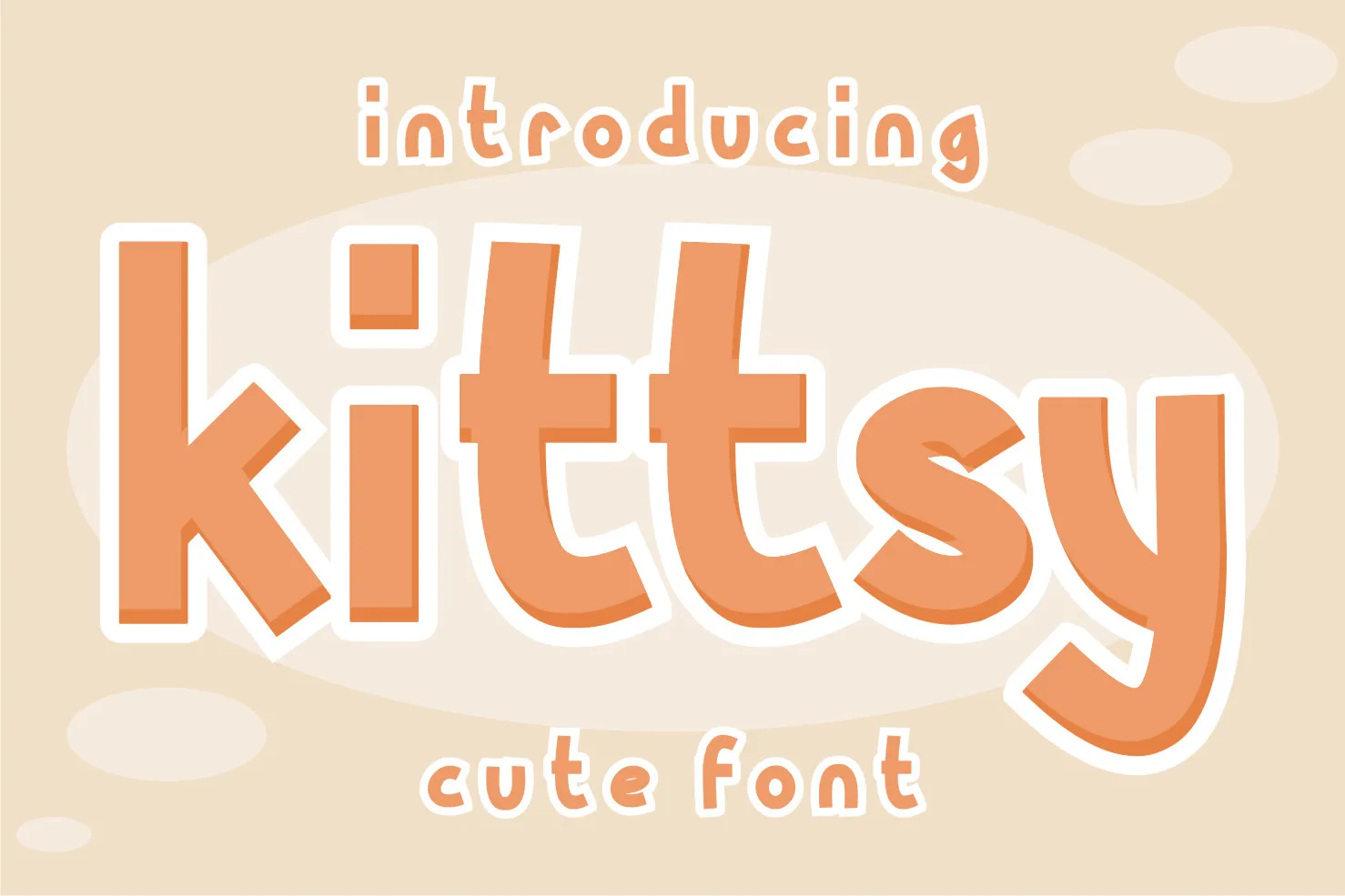
Kittsy Display Font – Fonte Grátis
Kittsy Display Font
Esta é uma fonte de exibição alegre e amigável. Seu estilo suave e cheio de vida a torna uma escolha perfeita para iluminar seus designs. Através dela, você pode trazer um toque divertido e colorido aos seus projetos gráficos. Com certeza encaixa-se bem em qualquer design que exija um ar descontraído e brilhante, seja para títulos, headlines ou até mesmo pequenos detalhes decorativos. A fonte “Kittsy Display Font” de letrafiastudio é a escolha perfeita se você procura algo divertido e vivaz para enriquecer seu trabalho gráfico.